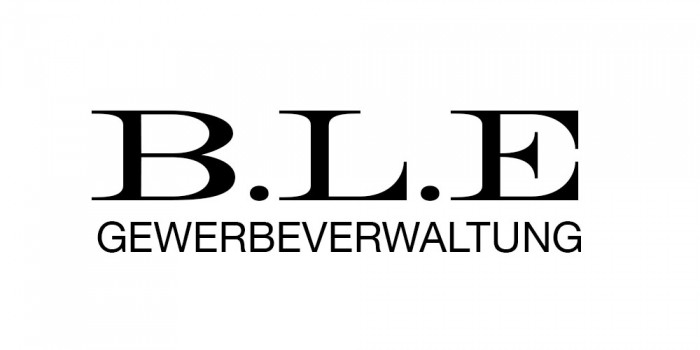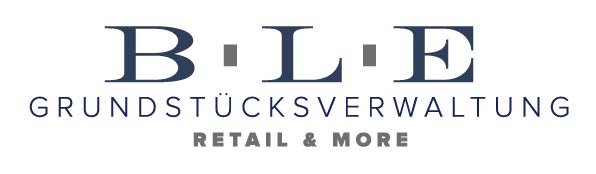
Suche Sans Serif Schrift passend zu HWT ROMAN EXTENDED LIGHTFACE REGULAR
Ich bin auf der Suche nach einer Sans Serif Schriftart für eine Logounterzeile, die auch als Fließtext dienen soll, die zur Hauptschrift im Logo passt.
Im Logo habe ich die Schrift HWT ROMAN EXTENDED LIGHTFACE REGULAR (Adobe Typekit) genutzt.
Im Beispiel ist die Unterzeile in Helvetica Neue gesetzt. Passt die vielleicht schon oder gibt es bessere Alternativen.
bessere alternativen gibts immer:
vorallem würde ich die schrift leicht sperren (siehe: spacing) um den buchstaben mehr luft zu geben, das ließt sich dann auch in kleineren größen besser.
Vielleicht hatte ich es missverständlich geschrieben. Der Fokus liegt auf der HWT. Also eine Schrift, die zu den 3 Buchstaben passt. Sie muss nicht der Helvetica ähneln. Diese habe ich quasi als Platzhalter genutzt.
Es soll eine Schriftart sein, die gut zur HWT ROMAN EXTENDED LIGHTFACE REGULAR passt und auch als Fliesstext nutzbar ist. Der Helvetica braucht sie nicht ähneln.
Was bedeutet hier passen? Das gezeigte Bild ist schlimm, das paßt wie die Faust aufs Auge. Ich würde wohl nicht nach einer Serifenlosen suchen, die den drei Buchstaben ähnelt, sondern die einen deutlichen Kontrast bildet, also eher eine schmale. Der Anfang der Zeile ist schwierig wegen der Serifen des B. Wo ist denn der eigentliche linke Rand des Bildes? Ich würde darüber nachdenken, einen Block zu vermeiden, also noch anders als die beiden Beispiele. Mit gemischter Schreibweise kann die Zeile recht kurz werden und an die rechte Kante vom E gestellt werden. Dann kann es vielleicht auch eine Kursive oder Schreibschrift sein. Blöcke sind in meinen Augen selten erstrebenswert, außer natürlich man arbeitet für Militärparaden in Diktaturen.
Leider habe ich mich wohl immernoch unverständlich ausgedrückt. Ich suche eine Schrift, die passt, gerne auch im Kontrast. Sie soll ihr nicht ähneln, ganz im Gegenteil, das würde sich ja beißen. :-)
Die Unterzeile habe ich nur schnell untergeschrieben, um zu zeigen, worum es geht. Handelte sich nicht um meinen Vorschlag. :-)
Ich hänge noch einmal meinen Entwurfsstand an. Hier habe ich als Unterzeile die Proxima gewählt. Ich bin mir nur nicht sicher, ob man diese Schriften mischen darf.